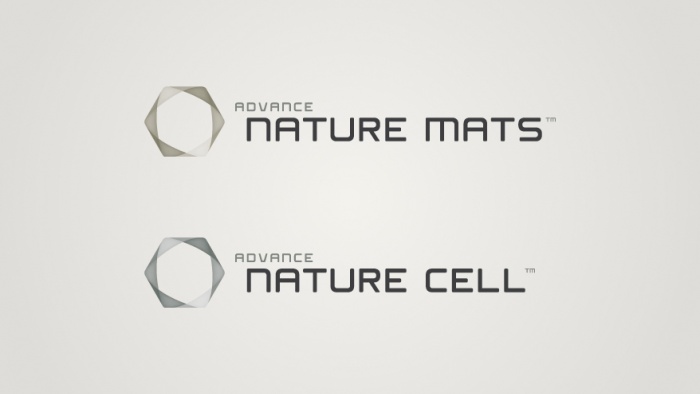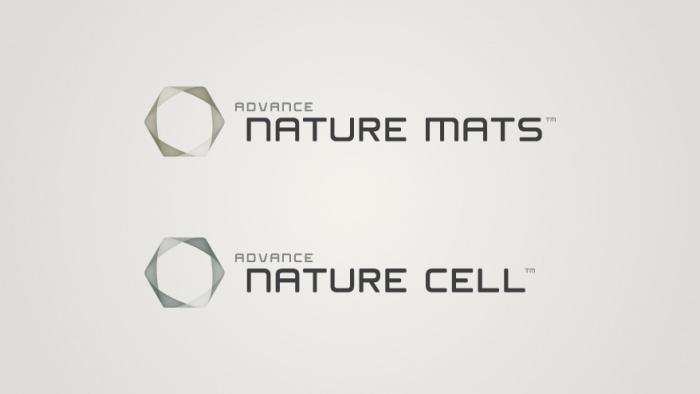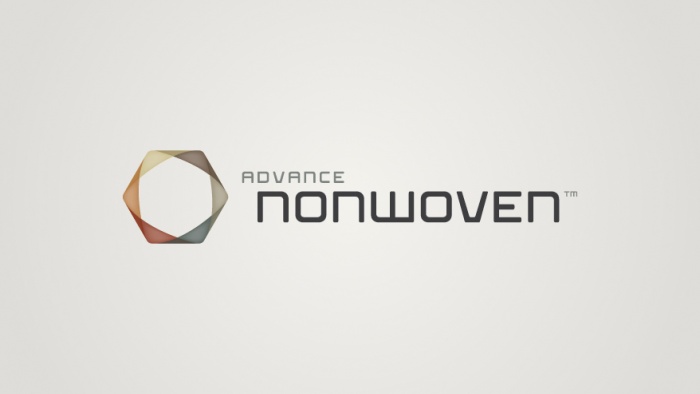
leider konnte mir bis jetzt keiner weiter helfen und sagen,
um welche schrift es sich in den folgenden bildern handelt ...
mir geht es im besonderen um den buchstaben "s", aber auch die gesamte wirkung dieser schrift.
habt ihr alternativen für mich die entweder in die richtung dieser schrift gehen oder fallen euch schriften ein
bei denen das "s" mit diesem hier vergleichbar ist?
So ein S hat zum Beispiel die Handel Gothic. Und bzgl. Deiner Vorlage gehen diese in eine ähnliche Richtung:
Vielleicht findest Du hier aber noch passendere:
Des Weiteren könntest auch noch mal whatfontis, etc. »befragen«.
Könnte aber genauso gut sein, dass die drei eckigen Wortmarken selbst konstruiert wurden.